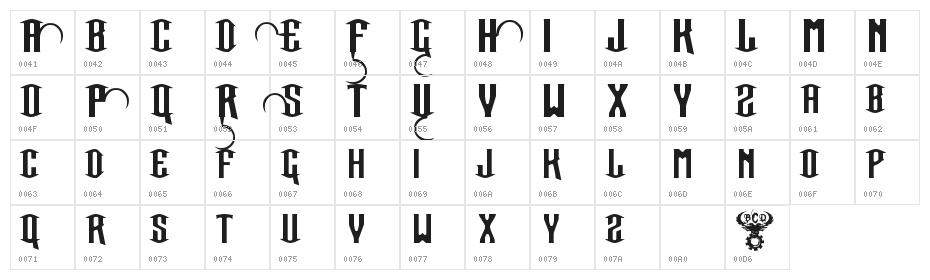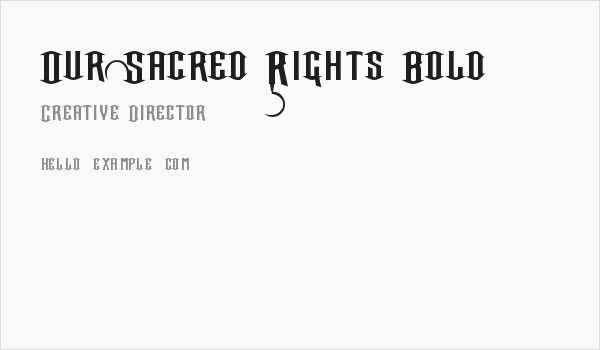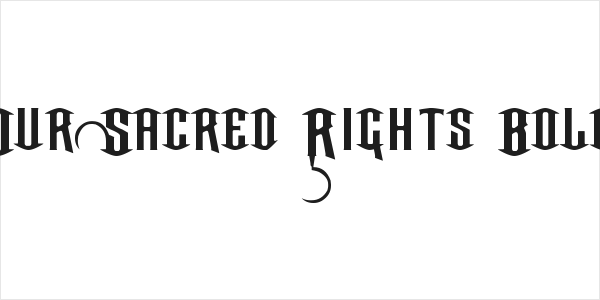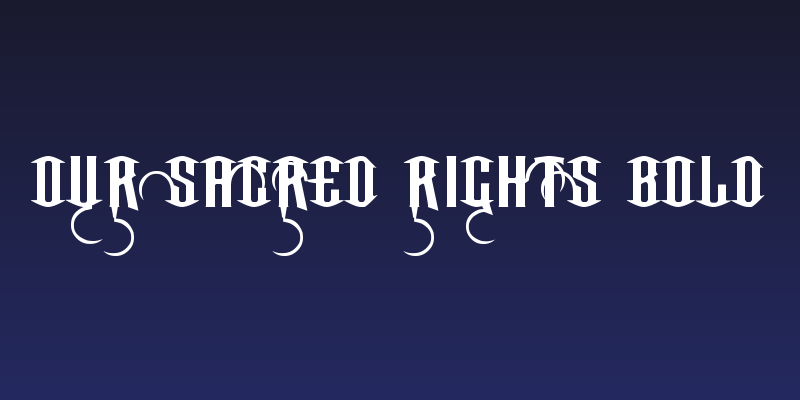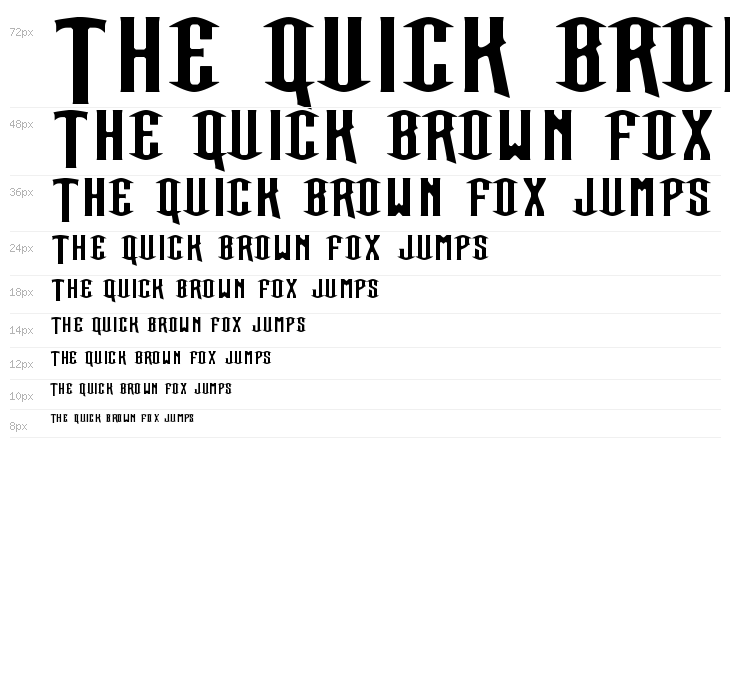
Our Sacred Rights Bold Font
| Proiecte propuse | Ideal for use in branding, posters, book covers, or any project requiring a historical or authoritative aesthetic. |